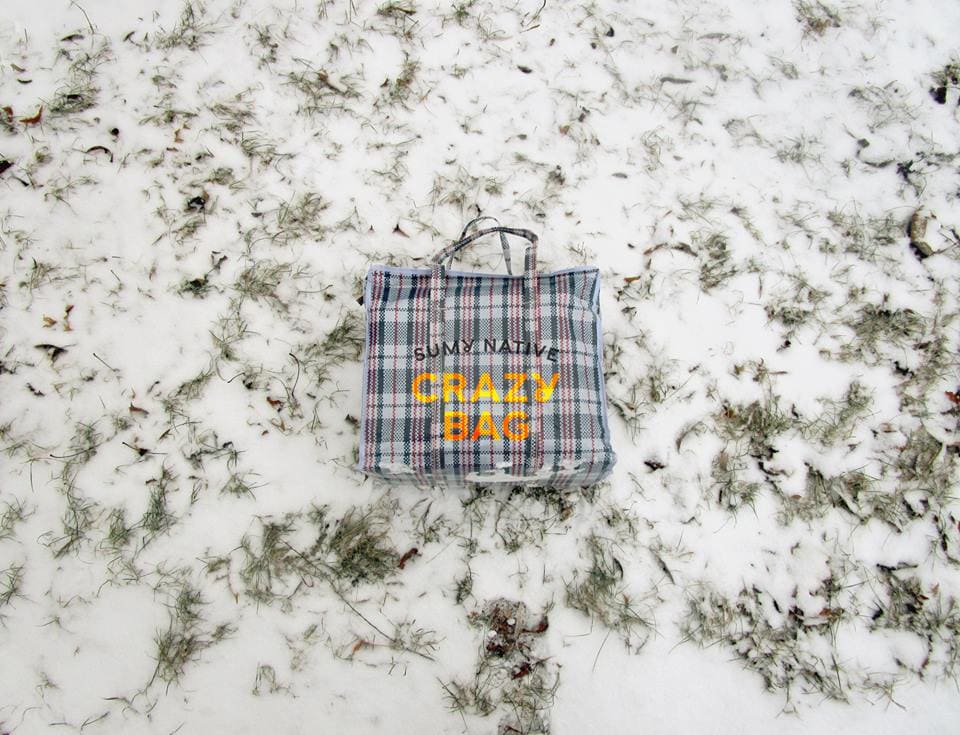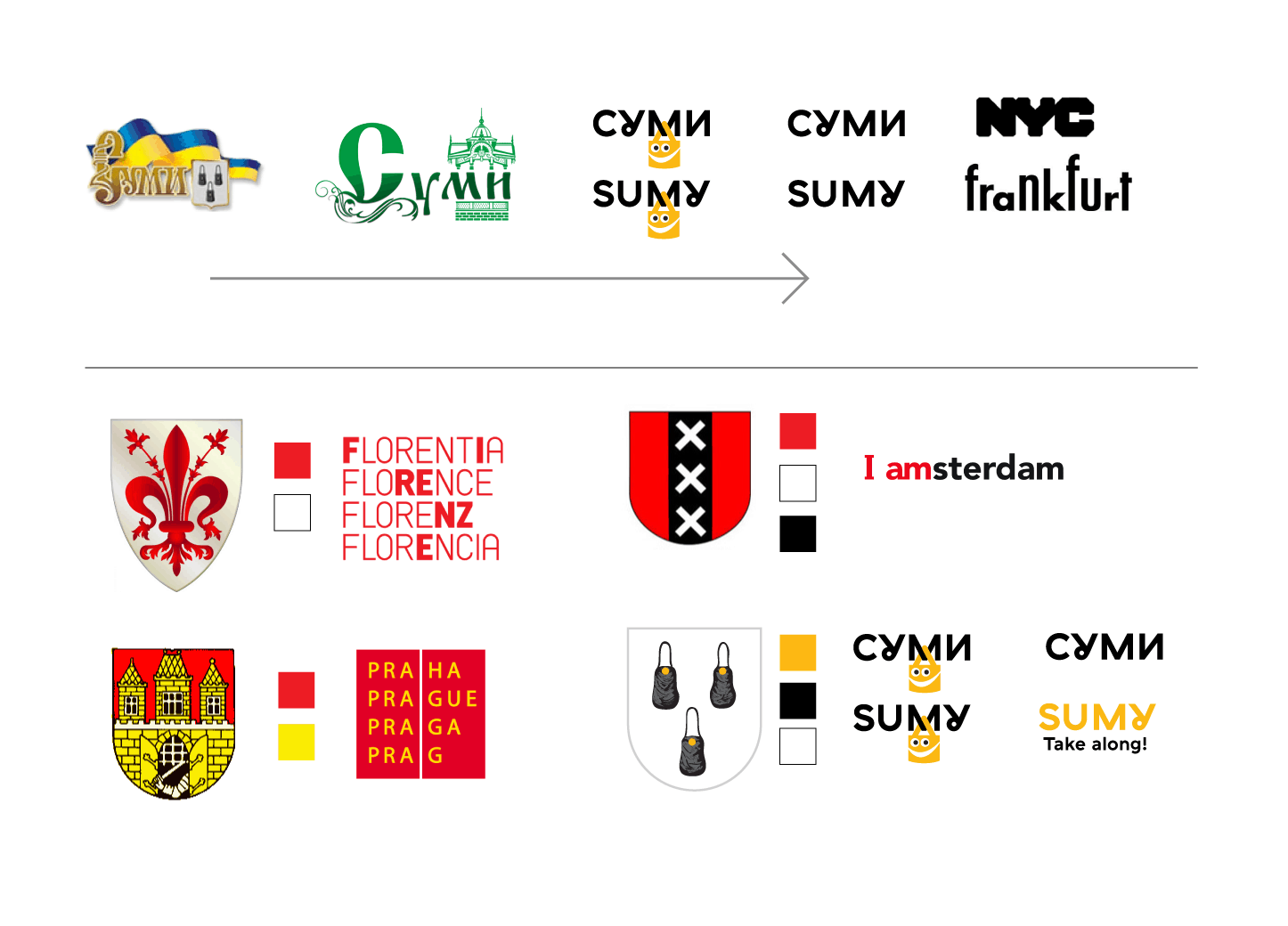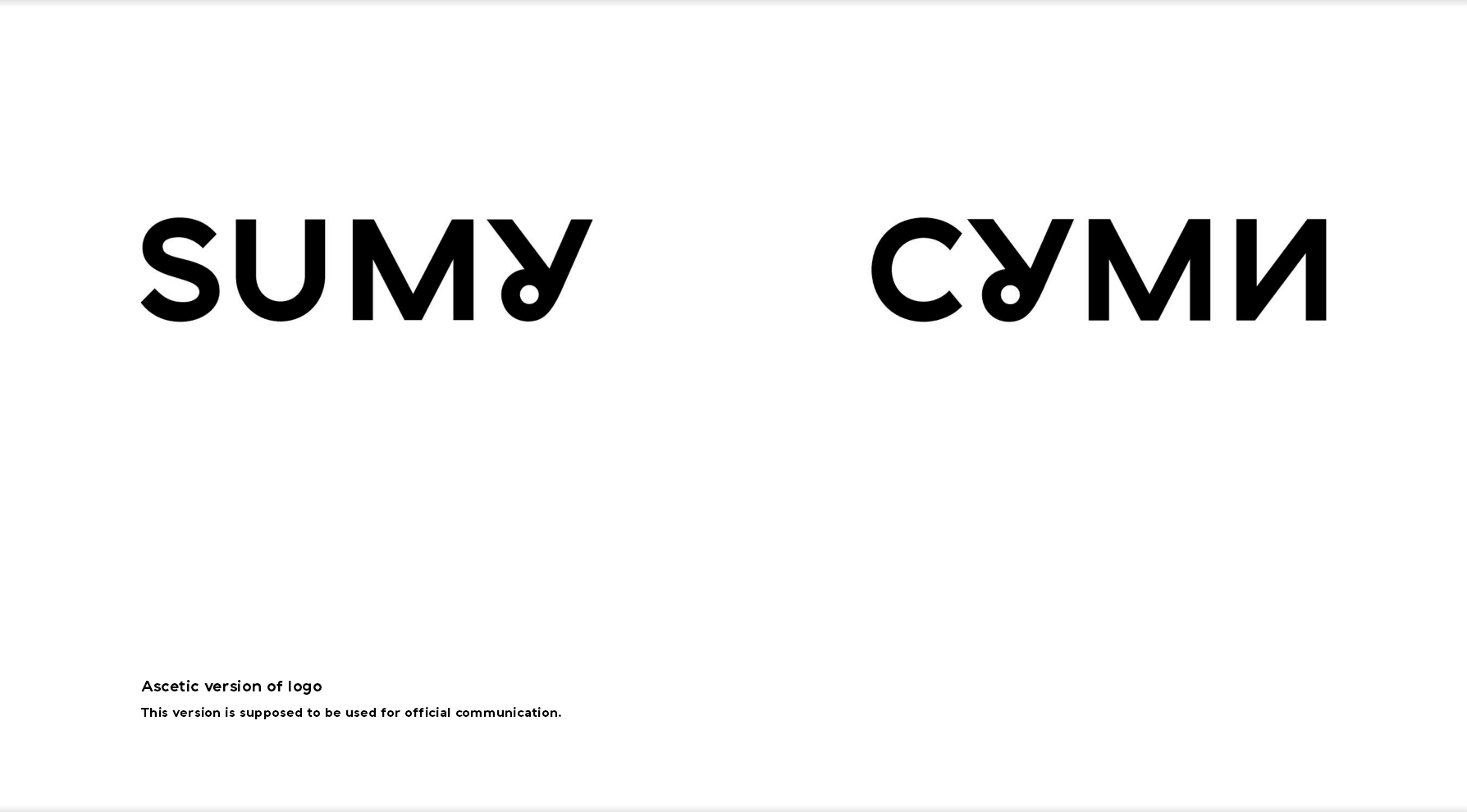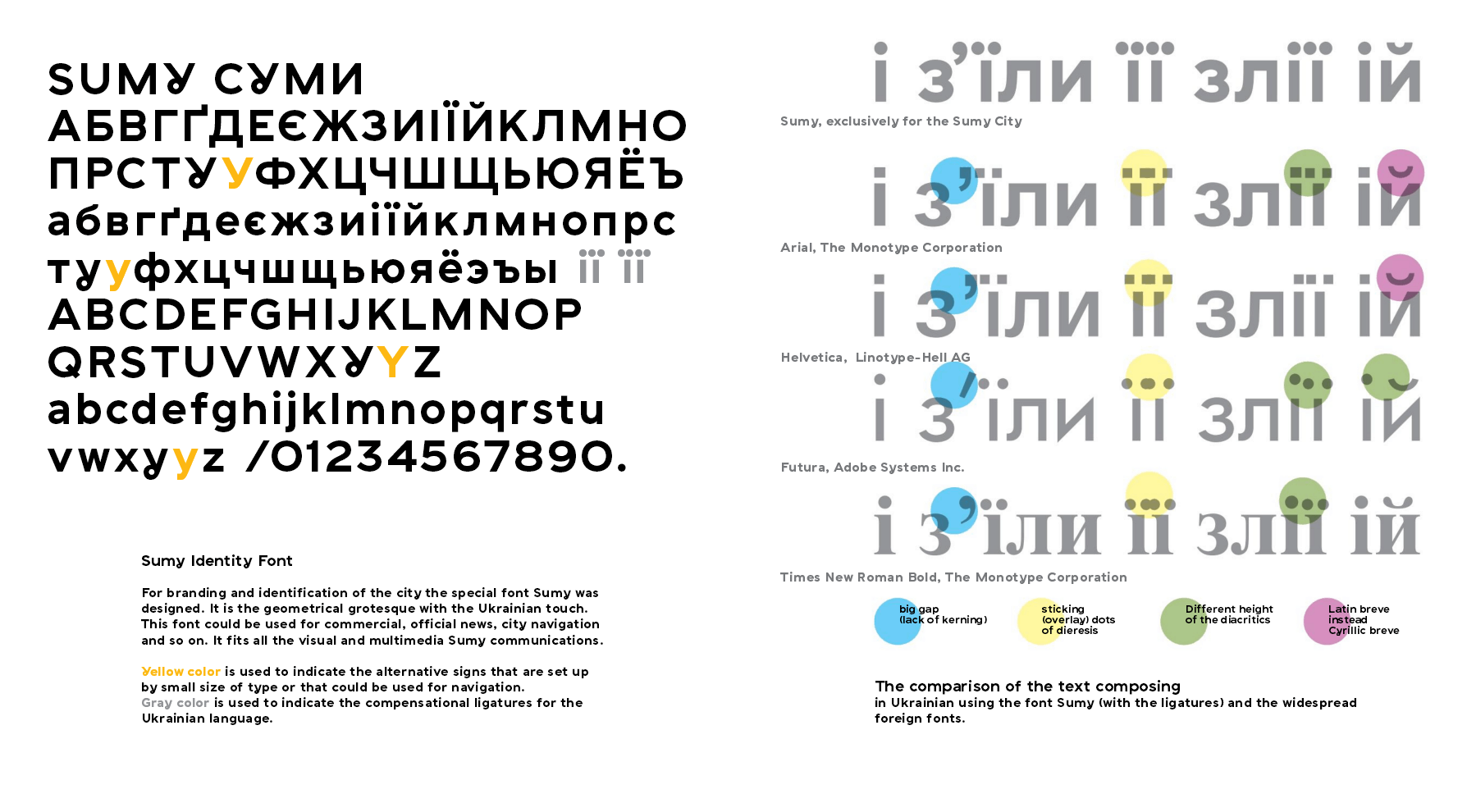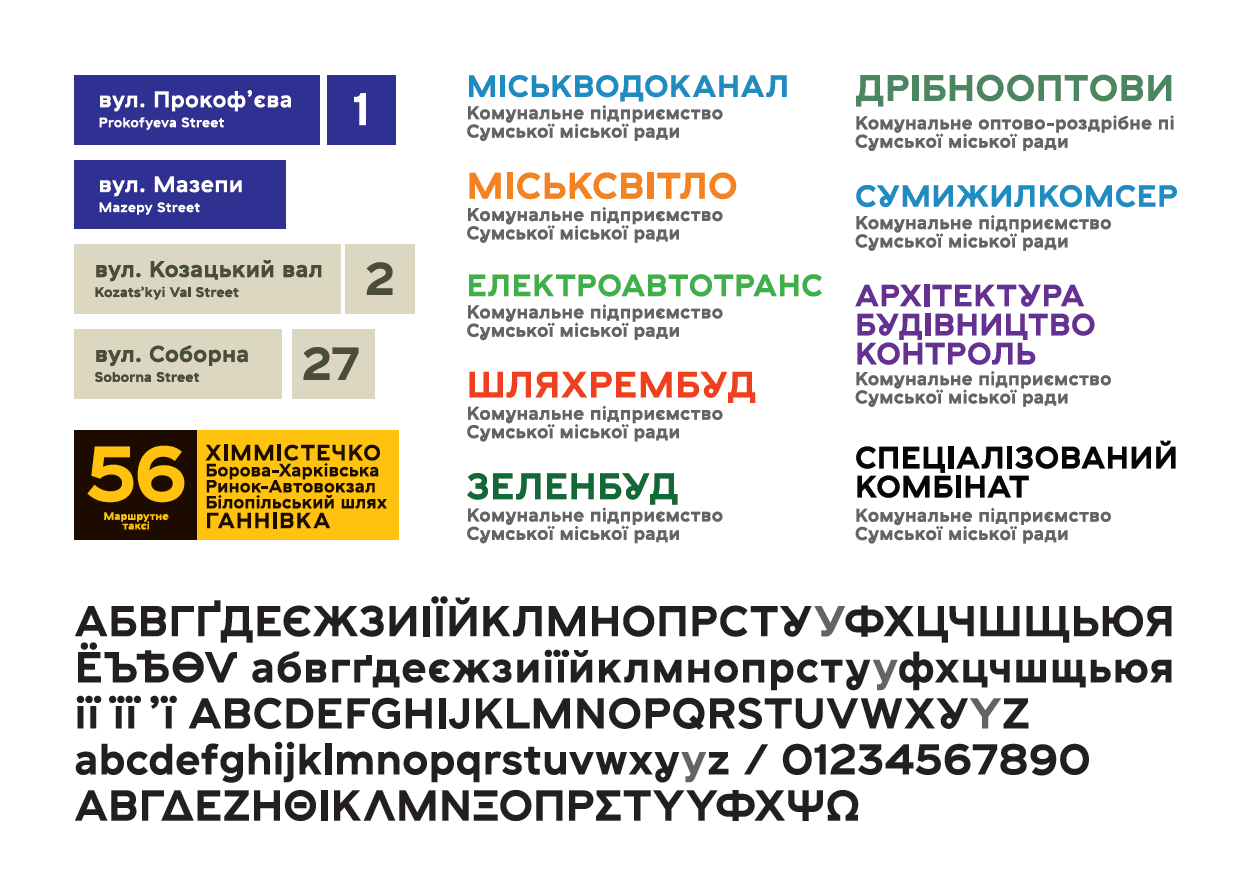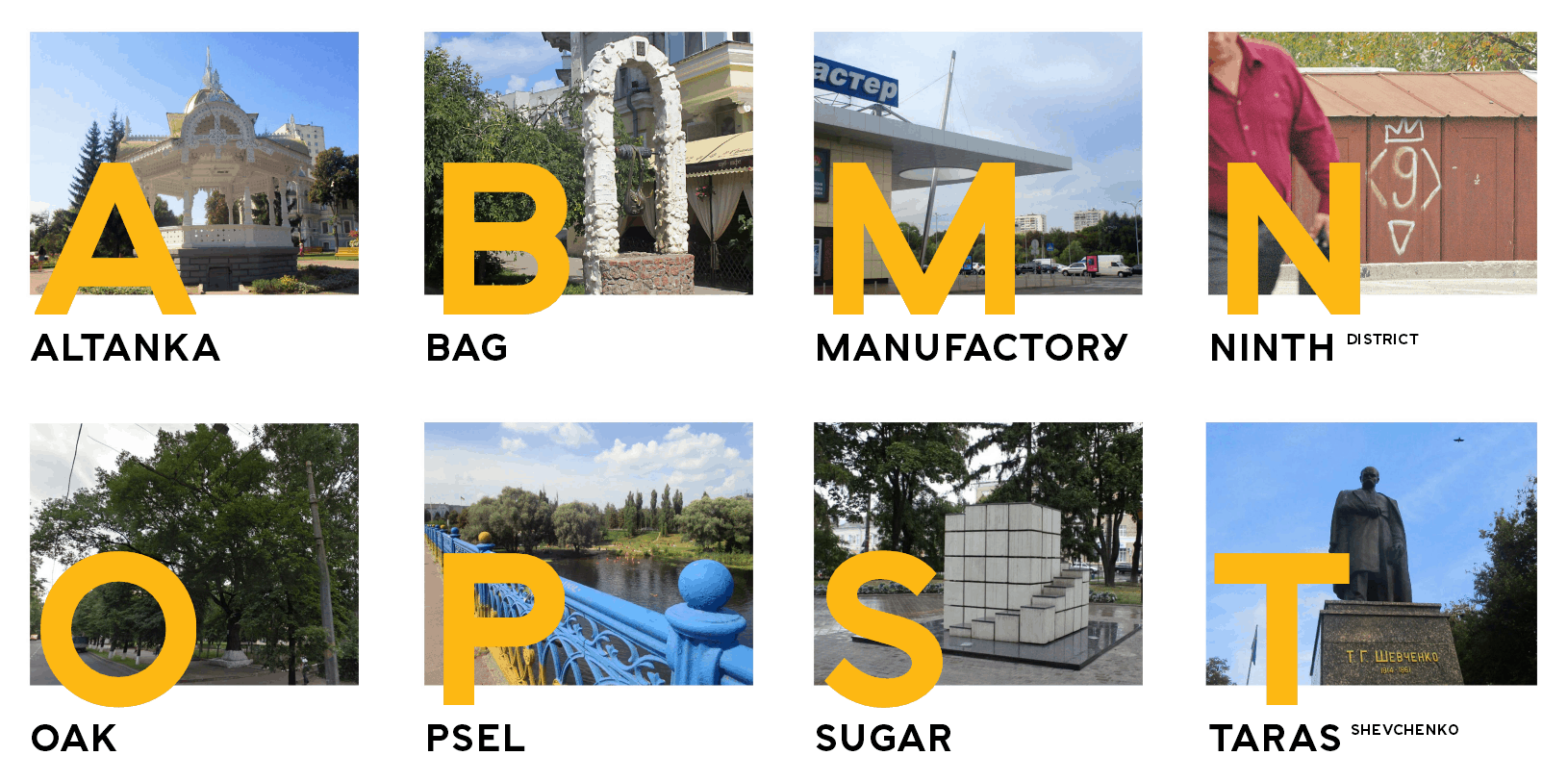
Я взялся за создание фирменного шрифта для Сум по простой причине — я здесь живу. Разработка шрифта — моя инициатива, но в рамках внешнего посыла. Летом 2016-го года городские власти Сум организовывали конкурс на создание логотипа города. Фирменный шрифт был частью предложенного проекта фирменного стиля города.
В идеале, хотелось, чтобы написание СУМИ / SUMY фирменным шрифтом и стало логотипом города. Чтобы было чисто шрифтовое решение, как в тех же Нью-Йорке, Франкфурте или Флоренции.
А любая надпись этим шрифтом могла ассоциироваться с городом.
Шрифт Sumy вырос из другого моего проекта — просто навигационного шрифта, который я делал. Это шрифт с простыми геометрическими формами, отсылающий к эстетике дорожных знаков.
Помогали опубликованные исследования по навигации, хорошие западные аналоги. Кроме того, помнится, ещё в детстве, когда бывал у мамы на работе, часто листал книжку “ГОСТ 10807-78 Знаки дорожные”. Там в конце были представлены чертежи букв для указателей – мне они очень нравились, мог часами их рассматривать, что-то перерисовывал. В общем, давно интересуюсь этой темой, в моём случае это уходит корнями далеко.
По задумке шрифт для Сумм должен был выполнять две функции – использоваться в навигации (быть нейтральным, не отвлекать на детали) и в фирменном стиле города (быть узнаваемым). Поэтому в рамках одного шрифта существует две формы буквы У: обычная (для навигации) и узнаваемая — с петелькой.
Буква У шрифта Сум наиболее узнаваема, визуально выделенная буква в шрифте, играет роль якоря внимания. Внешний вид У воспроизводит традиционные украинские формы. По своей форме У также напоминает форму места, где исторически были основаны Сумы. Козацкая крепость, которая расположена на перекрестке рек Сумы и Сумки.
Также в шрифте практически отсутствует контраст (разница между вертикальным и горизонтальным штрихом), широкие треугольные (А, У, М, V), оптические компенсации сведены к минимуму. В общем, я хотел сделать лаконичный и узнаваемый шрифт.
Как мне кажется, проект фирменного шрифта для Сум несколько опередил своё время/место. По крайней мере, в головах чиновников. Хотя моя работа и была признана одним из победителей того конкурса, найти взаимопонимания с городскими властями не удалось. Может, чуть попозжее это станет актуальным.
Сейчас шрифт если и используется, то в неофициальных проектах:
Выставка живописи. Афиша
Сообщество Smart Sumy
Паблик для местных Crazy Bag
Постер шрифта Суми на выставке “Живий шрифт” (Книжновий Арсенал 2017)
Однажды мне пришло еще одно предложение сделать шрифт для одного региона Украины, было достигнуто принципиальное согласие, но потом заглохло как-то. Может, в будущем актуализируется. Поживём – увидим.
В мае 2014 года я выпустил в продажу шрифтовую гарнитуру Proba Pro — геометрический, но слегка гуманизированный гротеск по мотивам гротесков 1920-х годов. В ноябре ко мне обратился основатель инициативы «Агенти Змін» Игорь Скляревский с предложением доработать гарнитуру, чтобы сделать ее пригодной для использования в городской навигации.
Киев — практически мой родной город, я прожил в нем больше двух третей жизни (до этого жил в Таллинне, Эстония). Мне небезразлично, как он выглядит, и естественно, хотелось в рамках своей компетенции принять участие в улучшении его внешнего вида.
По сути, выбор характера шрифта был не за мной, а за Игорем, который сам выбрал “Пробу Про” в качестве основы для навигационного шрифта. Естественно, он потребовал определенных доработок, главной из которых было увеличение высоты строчных букв (x-height).
Также появилась альтернативная форма цифры 3 для усиления отличия ее от буквы З, и был внесен ряд правок по формам некоторых букв.
Сейчас шрифт используется во всех городских проектах Агентів Змін: схемы, экраны, плакаты в метро, адресные таблички. Очень много проектов «Агентів Змін» находится в работе, поэтому продолжение внедрения шрифта обеспечено.
Спрос на шрифт для города — очень непредсказуемая вещь. Конечно, я был бы рад принять участие в создании еще какого-нибудь украинского городского шрифта, если появится такая возможность.
Шрифт для міської навігації Львова з’явився у 2007-2009 р. в рамках грантового проекту по створенню туристичної інформаційної інфраструктури. Я був арт-директором і дизайнером цього проекту. Ми працювали над вказівниками, туристичними картосхемами міста, табличками з назвами вулиць. Крім того, було розроблено багато друкованої продукції і навіть автомобільна навігація. Після довгих пошуків нам так і не вдалося підібрати існуючий шрифт, який би повністю вирішував наші задачі, тому найлогічнішим рішенням було спробувати створити все з нуля.
Хоча, насправді, цей шрифт почався трохи раніше. В свій час я захопився вивченням довоєнних фотографій Львова, в яких мене привабили старі рекламні написи на стінах будинків. Я зауважив, що переважна їх більшість виконана практично одним і тим же виразним геометричним гротеском. Мінялись пропорції, товщини штрихів, але спільною була логіка побудови літер.
До речі, багато з тих написів і зараз видніються на стінах з-під шарів фарби. Я загорівся ідеєю створити на основі цього шрифту власний. В той час мені дуже допоміг порадами Геник Заречнюк, за що я йому вдячний.
Коли в мене було готово кілька ескізних варіантів латинки й кирилиці, я запропонував використати ці літери для міської навігації. Ідею підтримав Василь Косів, дизайнер, на той час завідувач кафедрою графічного дизайну Львівської національної академії мистецтв і, за сумісництвом, заступник міського голови Львова. Згодом до роботи приєднався Юрко Крукевич, чудовий ілюстратор і дизайнер, та Михайло Царик, який працював над картосхемами.
Олдскульний геметричний гротеск, який у мене був на той час, мав цікавий характер, вписувався в історичне середовище, але зовсім не підходив для навігації. Тому, після кількох ітерацій, шрифт повністю змінився: ми взяли пропорції і характер літер від старих історичних написів, одягнули це в гуманістичні форми і додали трошки навігаційності — відкритість, велика х-висота, малі виносні елементи. Останній варіант літер і додаткове, більш «навігаційне», накреслення намалював Юрко Крукевич. Також він намалював класні цифри, на основі старих табличок із номерами будинків. Так у нас вийшов перший в Україні міський шрифт, який був втілений у життя.
Згідно із загальноприйнятими європейськими стандартами для позначення об’єктів туристичного інтересу застосовується темно-коричневий колір.
Але для обґрунтування кольору знаків цього було не достатньо, тому для вибору оптимального варіанту було проаналізовано кольорову гаму елементів середовища центральної частини Львова.
Найбільше контрастують із встановленою домінуючою кольоровою гамою відтінки синього. Поєднання синього тла та білого тексту традиційно використовується для дорожніх вказівників, а вуличні таблички такого кольору широко поширені у багатьох містах світу. Але вулиці Львова перенасичені яскравими вивісками та рекламою, а таблички повинні не дисонувати, а навпаки —поєднуватись із середовищем. Тому, аби не збільшувати кількість агресивних елементів на вулицях міста, для фону таблиць було вирішено використати домінуючий колір середовища (насичений темно-коричневий), що, водночас, узгоджується із європейськими нормами з туристичного ознакування.
Шрифт на деякий час прижився, його почали використовувати у оформленні ділової документації, він увійшов в брендбук міста (хоча був не дуже пристосований до життя поза межами навігації). Зараз в комунікаціях Львівської міської ради його, як мені здається, почали витісняти традиційні «офісні» шрифти. Але я певен, якщо докласти зусиль і розвинути цей шрифт у повноцінну сім’ю з 4-5 накреслень, він буде чудово виконувати функцію одного з ідентифікаторів Львова.
Мене віддавна цікавить ідентифікація територій, зв’язок дизайну й простору, і зокрема, територіальні шрифти. Присвятив цій темі частину свого виступу на TEDxDonetsk (з 19-ої хвилини):
Раніше для проекту ідентифікації Харкова намалював шрифта ZionTrain. Чи не вперше в кирилиці спроектованого
навмисно для навіґації. Одним з накреслень шрифту можна користуватись безкоштовно за посиланням.
Також я звертався із пропозицією розробки шрифту до влади Запорізької області. Тому, отримавши пропозицію попрацювати над шрифтом для Маріуполя, радо на неї пристав.
Шрифт Mariupol є частиною ідентифікації цього міста, яку розробляв переможець відповідного конкурсу Сергій Родіонов. Він запросив мене до участі і, таким чином, проект став настільки озівським (приазовським) по духу, наскільки це можливо, адже Бердянськ, де я мешкаю, менш ніж в ста кілометрах від Маріуполя. Сергій, як автор цілого проекту, поставив чітко окреслене завдання і був арт-директором шрифтової частини. Крок за кроком ми розробляли, тестували, вносили зміни.
Шрифт Mariupol — це геометричний гротеск, натхнений, з одного боку, швейцарською та німецькою плакатною графікою, з іншого — сучасними технологічними гарнітурами San Francisco, Graphik, Walsheim. Доступний у трьох базових накресленнях: звичайному (Regular), напівжирному (Medium) та жирному (Bold). Також до комплекту додане спеціальне накреслення з піктограмами (Symbols). Підтримуються українська, англійська, грецька, російська мови.
Зараз шрифт офіційно представлено, його можна побачити і на маріупольських трамваях, і на бордах з привітанням міського голови. Ми сподіваємось, що присутність його в місті буде тільки зростати. Більше того, кожен охочий може завантажити цей шрифт і самостійно щось написати по-маріупольськи.
Такі проекти неможливо розробляти «в стіл», потрібна жвава участь міста або його представників. Зараз разом з Кирилом Ткачовим працюємо над шрифтом для вуличної навігації міста Дніпра. Сподіваюсь, що це не останній проект українського територіального шрифту, в якому пощастить взяти участь.